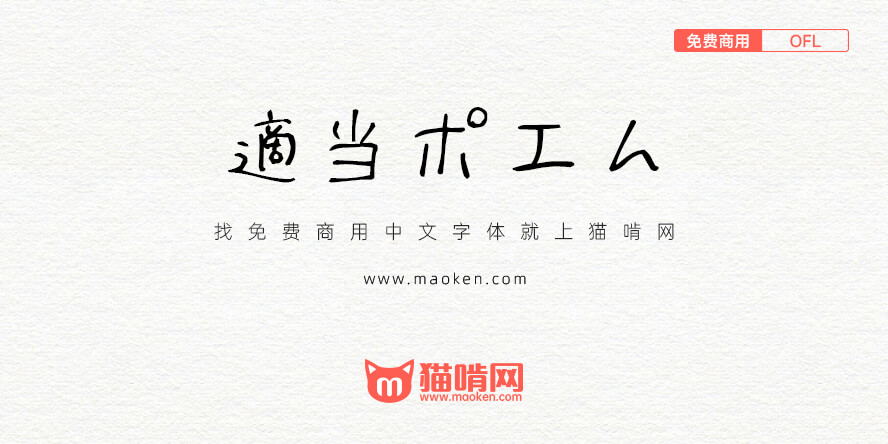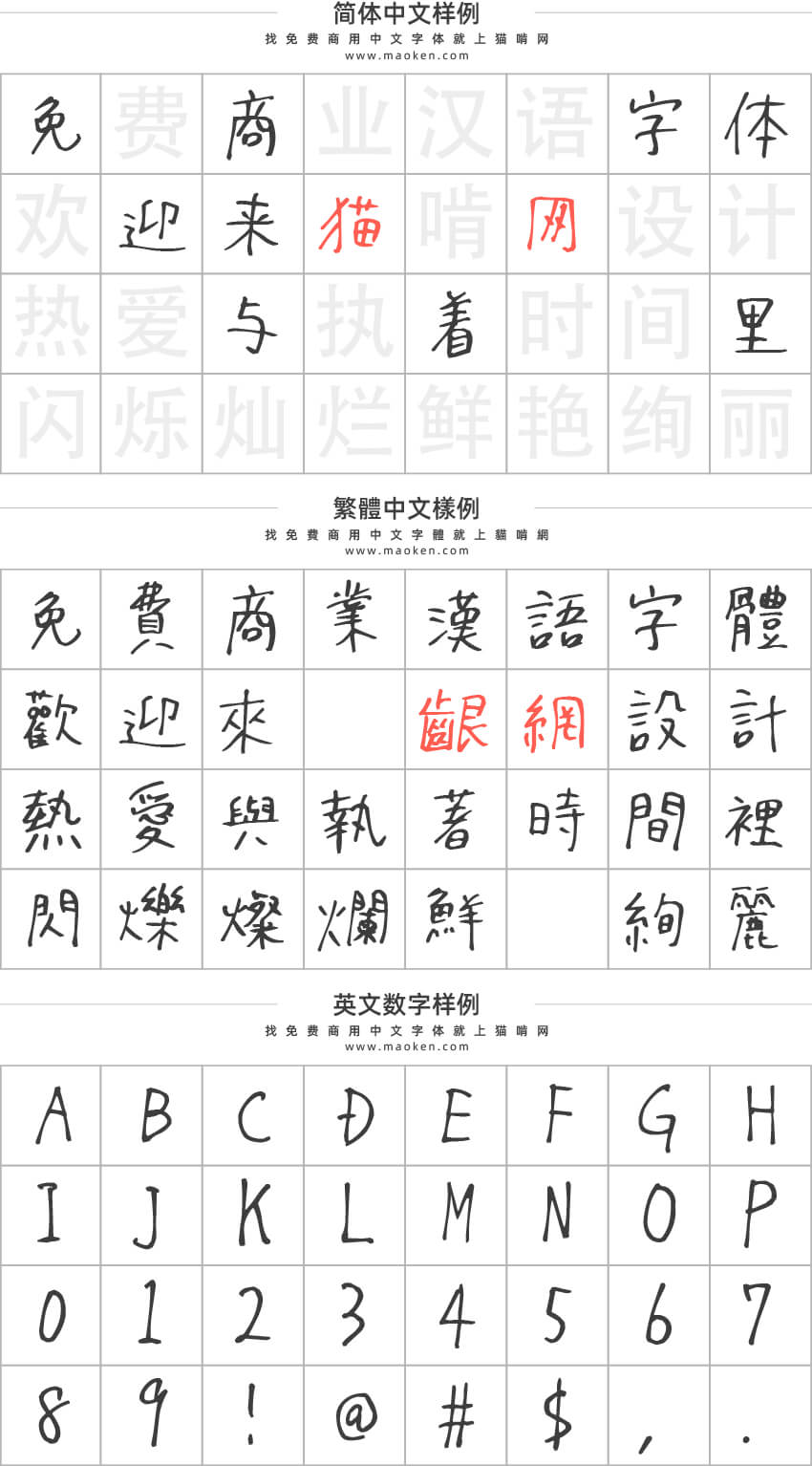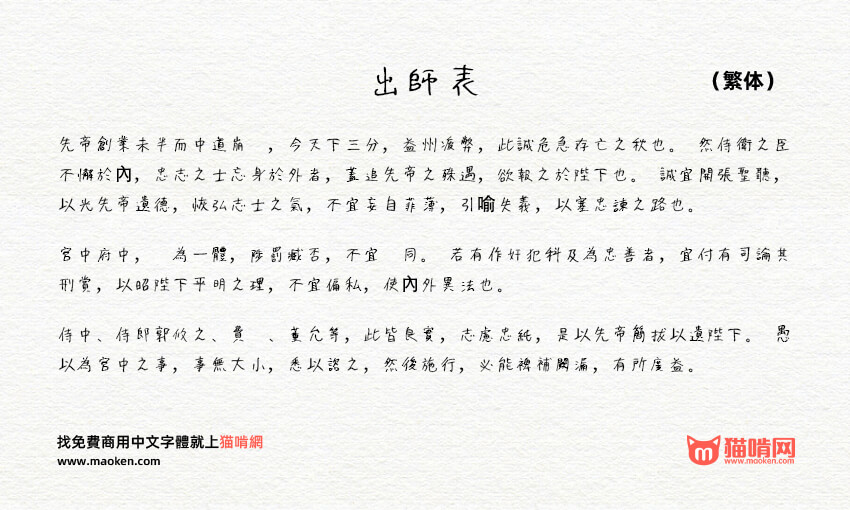
| 字体作者:Cockatrice Digital (日本) | 字体字重:4个 |
这是一款合适的日语手写字体。它收录了包括英文字母和数字、平假名、片假名、JIS第1至4级汉字以及其他汉字和符号等约16000个字符。这款字体适用于游戏、插图、动画、印刷品等多种用途。每个字符的大小和精细度都有所不同,呈现出独特的手写风格。